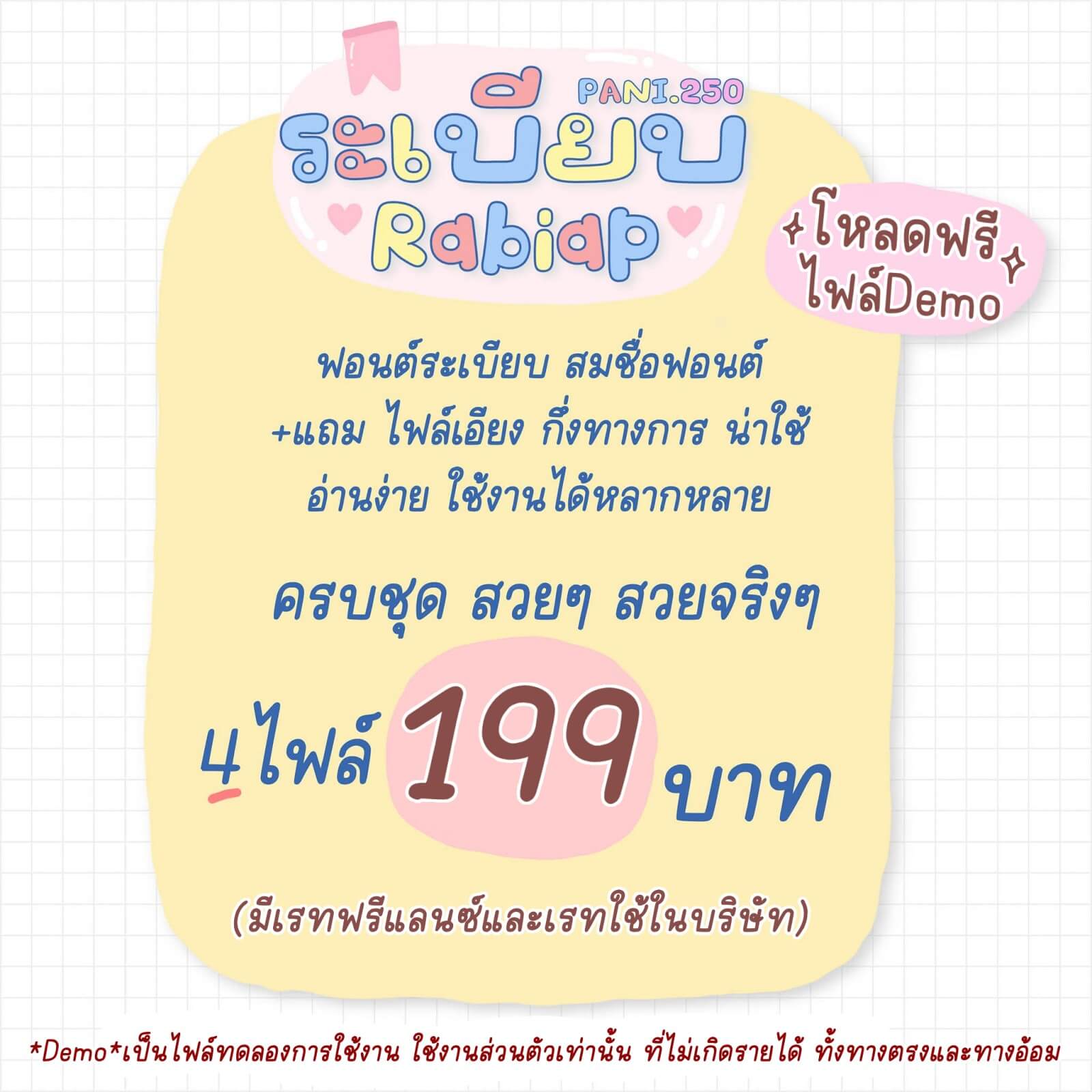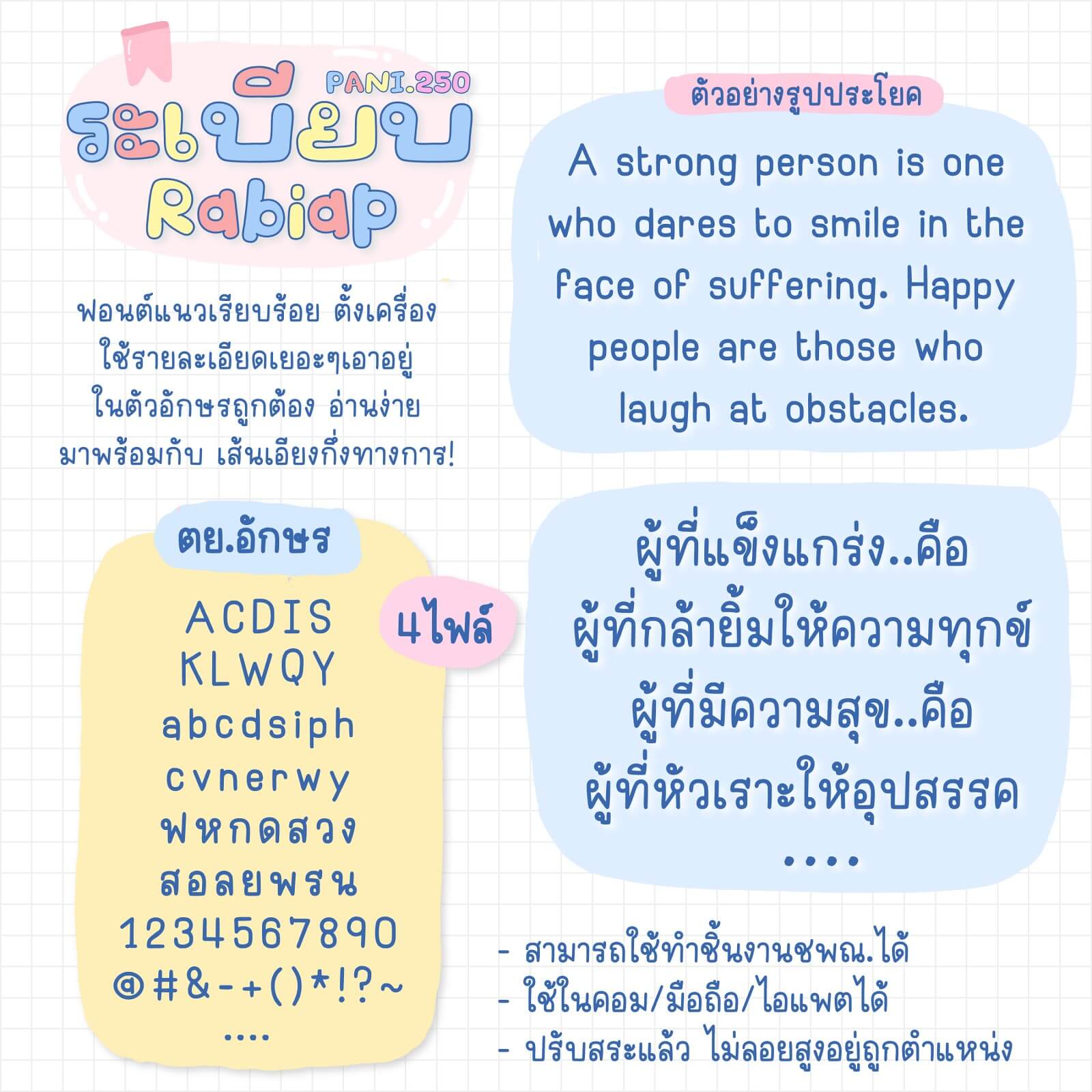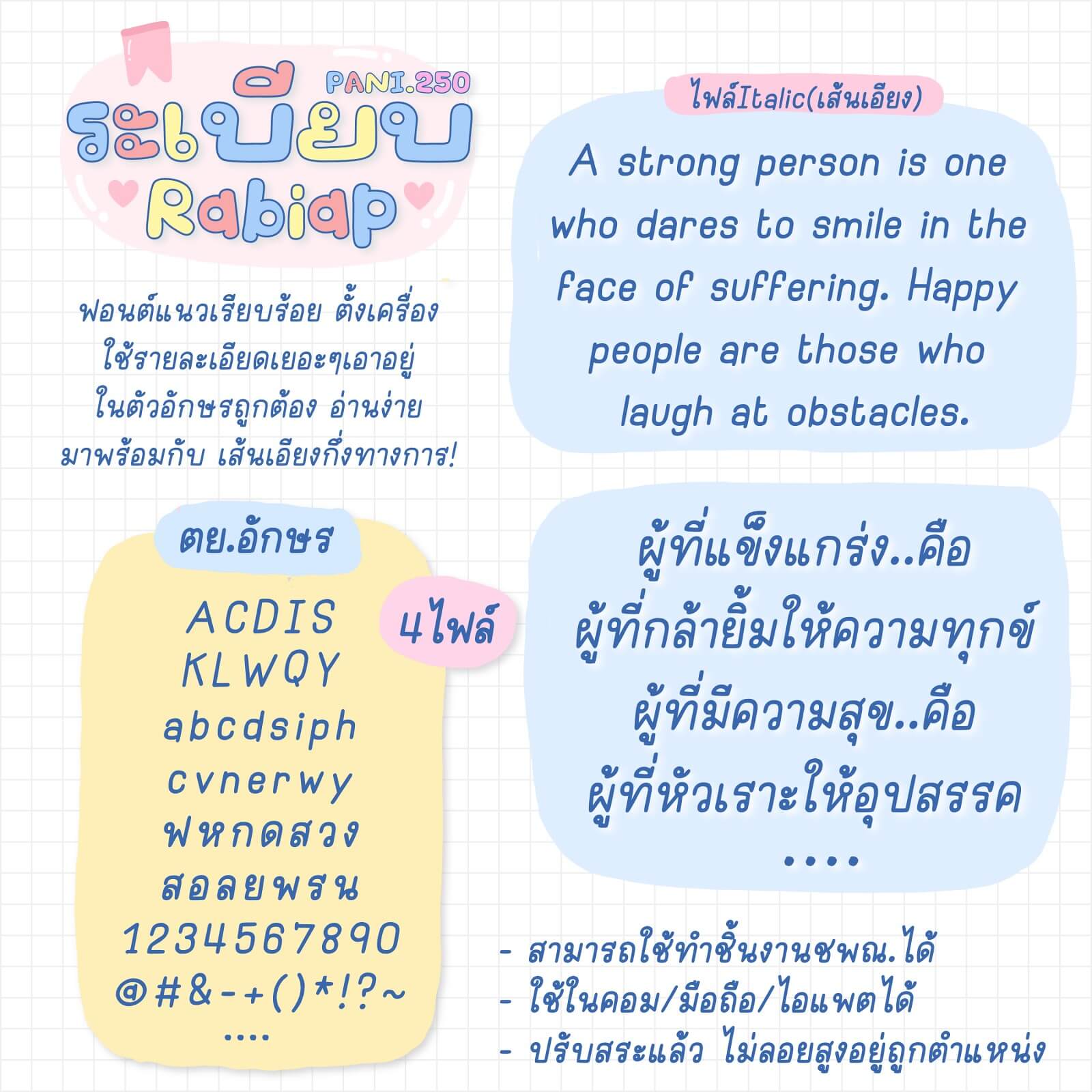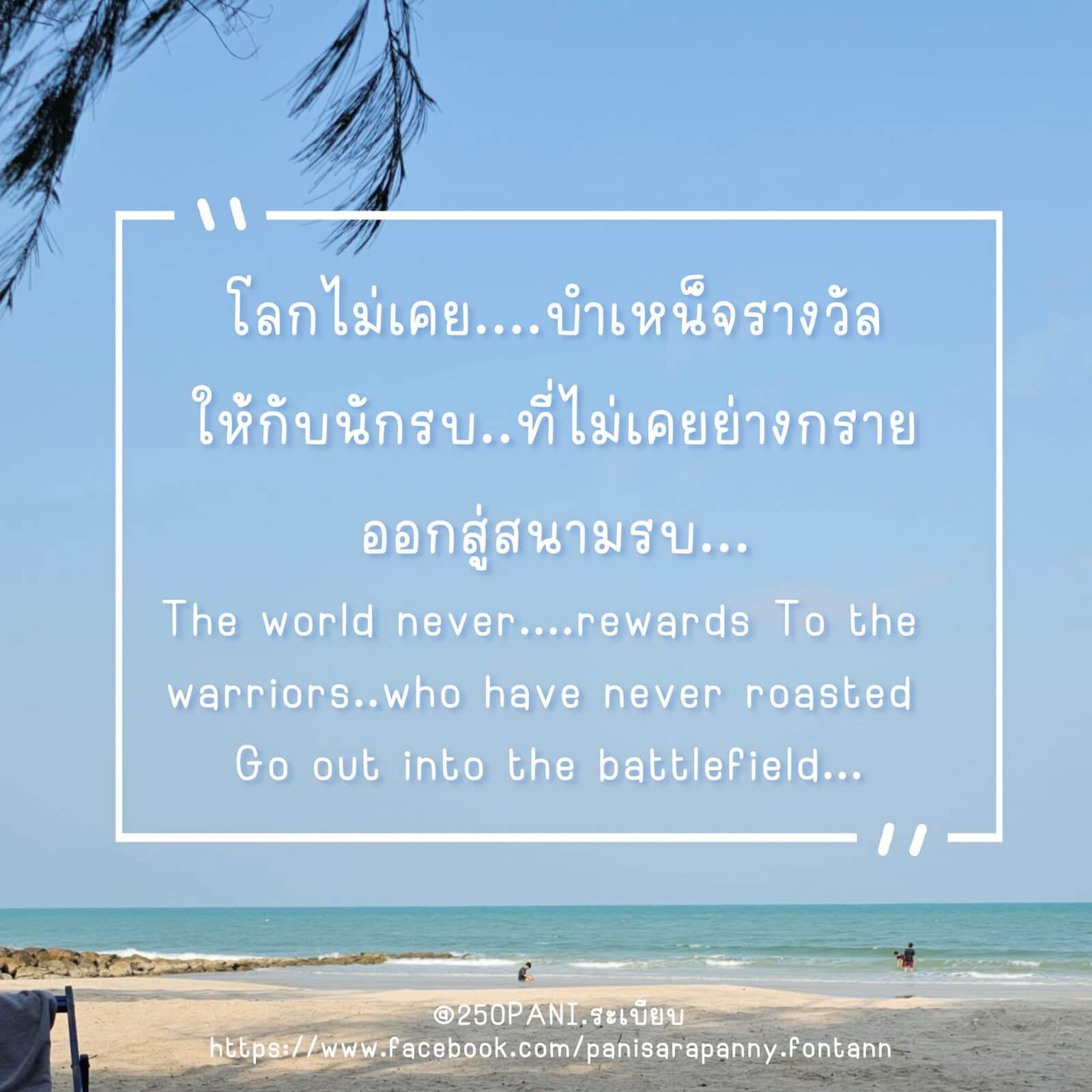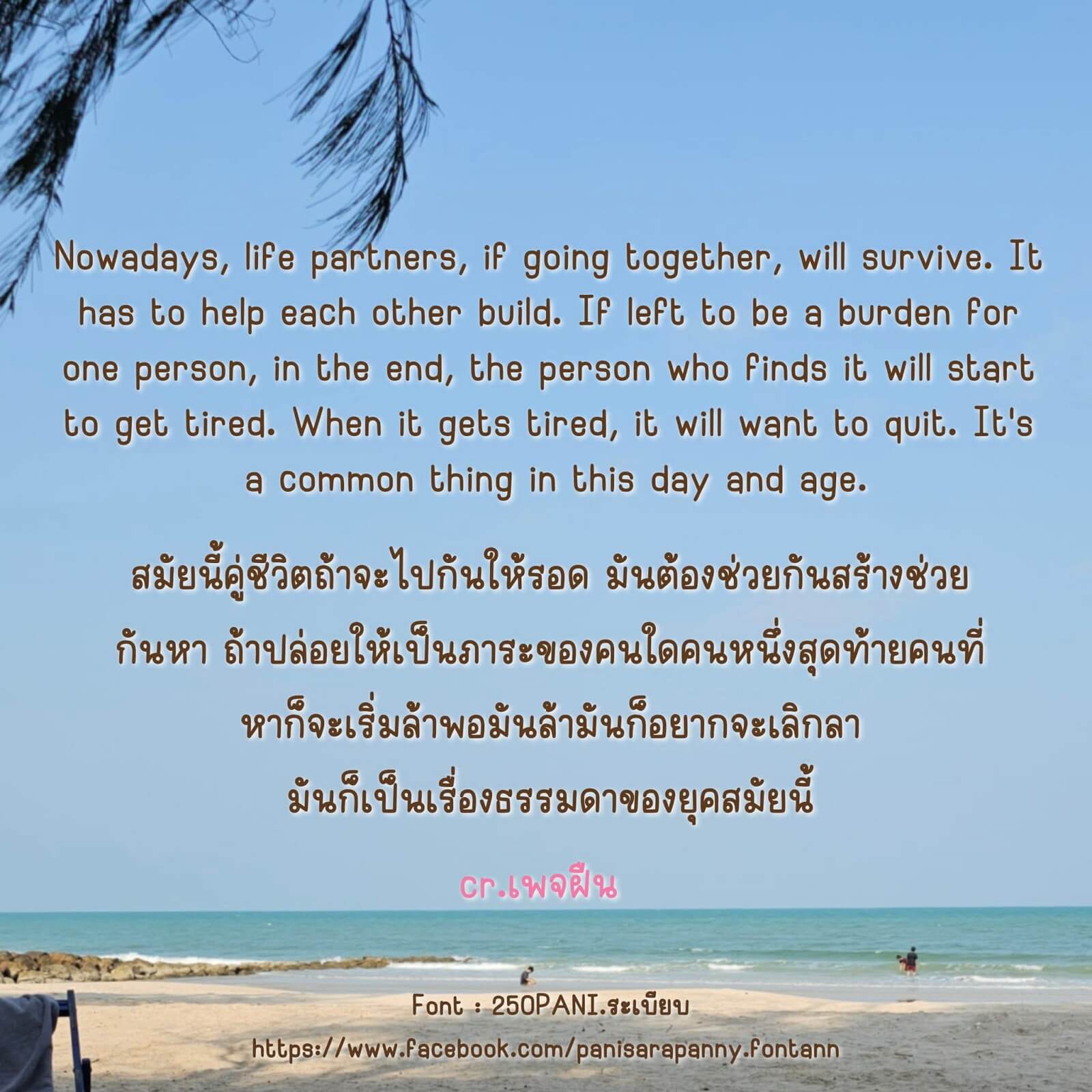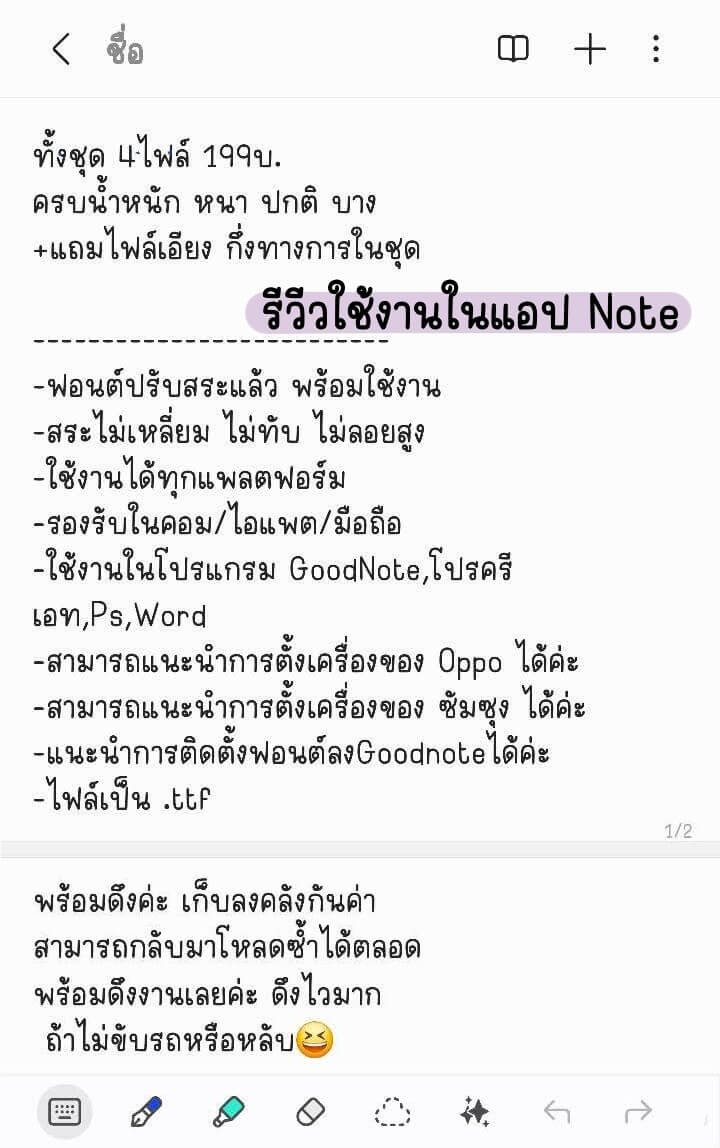
250PANI.ระเบียบ
ฟอนต์ 250PANI.ระเบียบ – ฟอนต์แนวเรียบร้อย ตัวกำลังดี ใช้งานรายละเอียดสวยมาก อ่านง่าย หรือใช้เป็นหัวข้อ หรือใบงาน ใครชอบแนวเรียบร้อยๆ แนะนำฟอนต์นี้เลยค่ะ ไม่ผิดหวังแน่นอน
+มาพร้อม ไฟล์ตัวเอียง ดูกึ่งทางการ ทุกอย่างดูกำลังดี ลงตัว
ฟอนต์มี 4 ไฟล์ – น้ำหนัก บาง ปกติ หนา ตัวเอียง